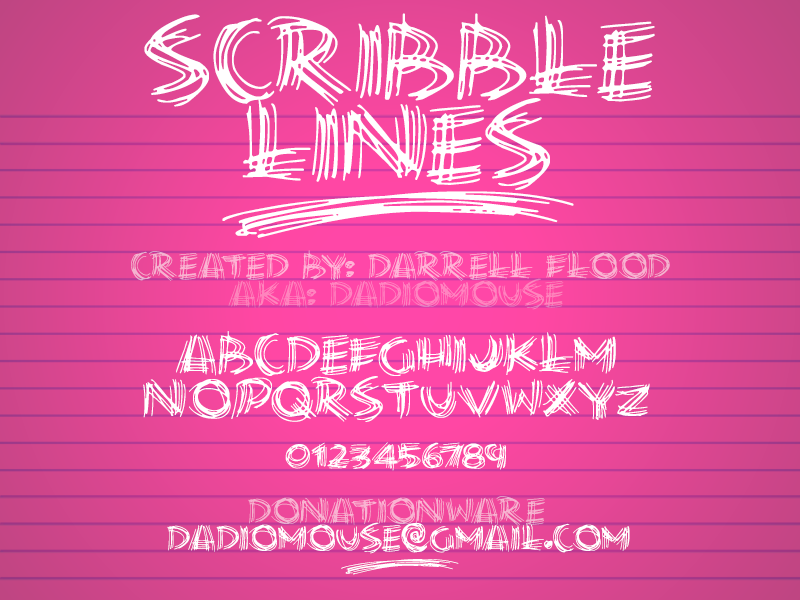
Scribble Lines Font – Download Grátis
A fonte Scribe Lines Font foi criada pelo designer Darrell Flood e é perfeitamente adequada para quem gosta de uma linguagem alegre e fluida nas criações digitais. Ela oferece um estilo suave e fácil de ler, ideal para desenhos livres ou gráficos de arte digital. Essa fonte Brush Fonts não apenas adicionará um toque único ao seu trabalho, mas também tornará sua produção muito mais atraente. Para quem procura uma opção gratuita com bom design, essa font é um excelente recurso. Embora ela seja gratuita para uso pessoal, o criador ainda aprecia qualquer doação que você possa fazer. Com uma simples aplicação de Scribe Lines Font em seu trabalho, pode-se adicionar um toque de personalidade ao mesmo tempo que preserva a conveniência e o estilo único dessa fonte. Sua versão gratuita ainda permitirá uma variedade impressionante de opções para trabalhos pessoais, desde desenhos até pequenos títulos. Afinal, quem não adoraria ganhar mais um recurso gráfico ao seu dispor sem ter que gastar nada? Siga a tendência da arte digital com a fonte Scribe Lines Font e traga um pouco de sua criatividade para cada trabalho que realiza.